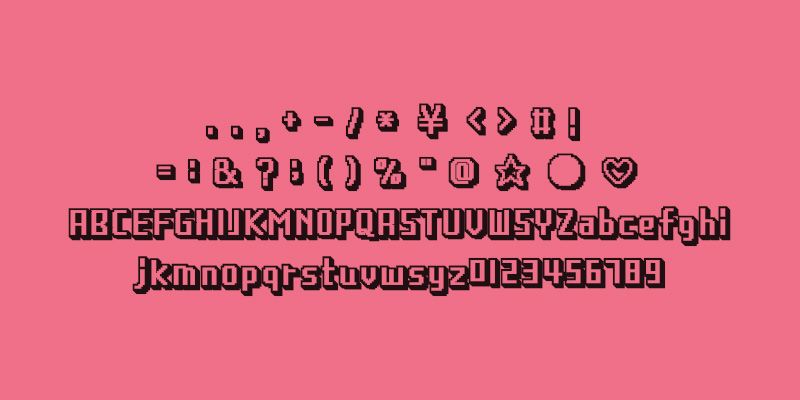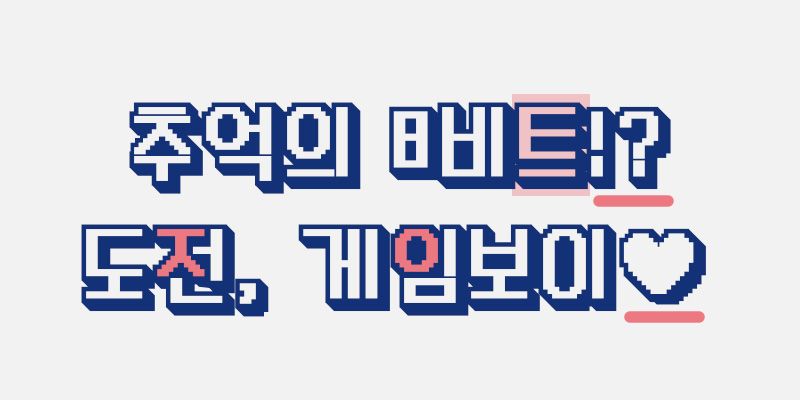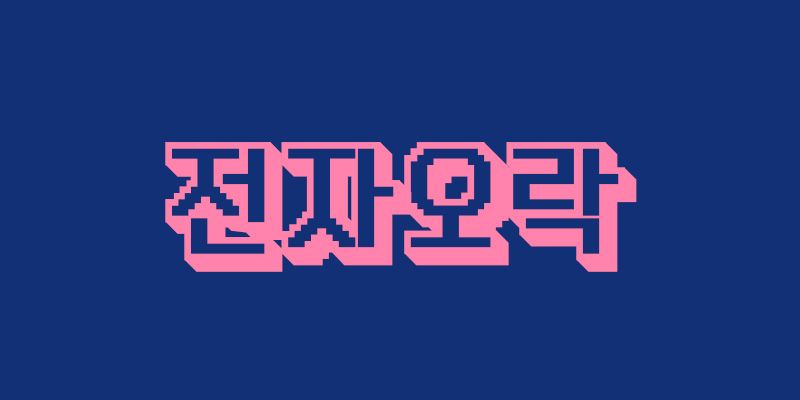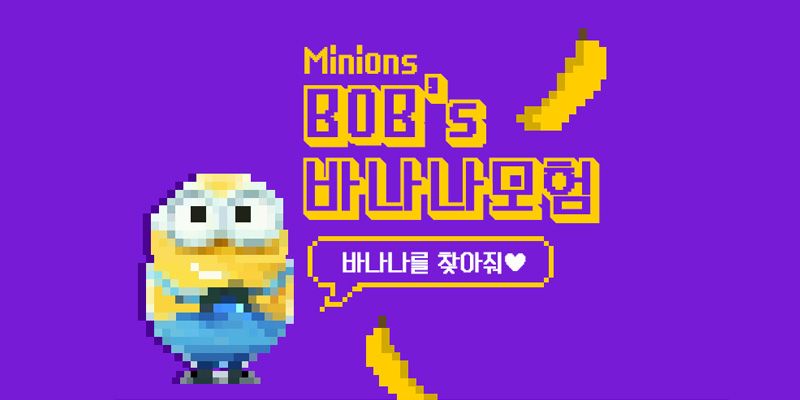
RixVideoGame ist eine Schrift für Titel mit Pixeln wie in 8-Bit-Videospielen. Sie hat eine variable Breite und eine quadratische Struktur, um eine Retro-Stimmung zu evozieren.